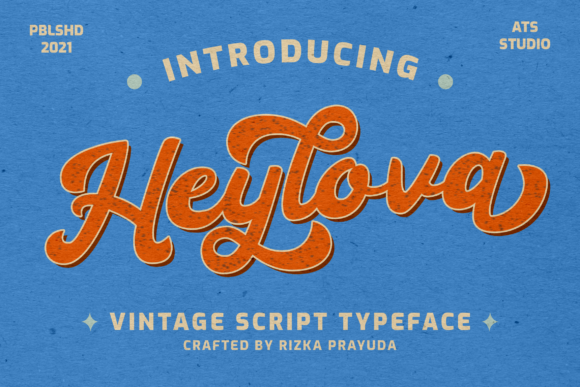
Creativefabrica Heylova Font
[Creativefabrica] Heylova Font
Гейлова - это великолепный, винтажный и смелый рукописный шрифт, созданный, чтобы придать стильный штрих вашим заголовкам и логотипам проектов.
Этот шрифт читается как сильный, уверенный и динамичный и может добавить тонны ностальгического характера вашим дизайнам.